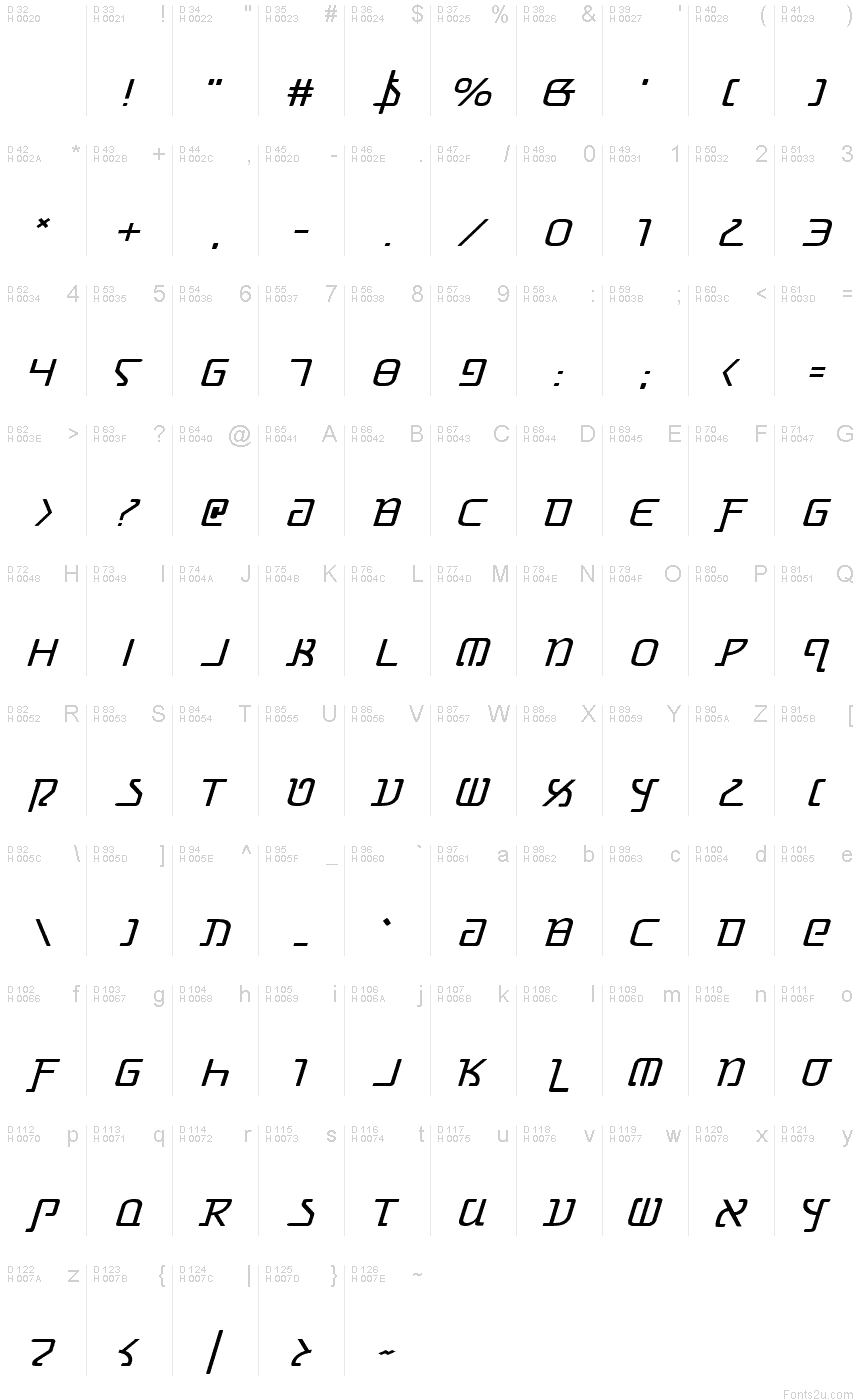
Grimlord Expanded Italic autorstwa Iconian Fonts to darmowy, futurystyczny krój typu display o szerokich, mocno pochylonych kształtach liter. Zaokrąglone zewnętrzne narożniki łączą się z przyciętymi łączeniami oraz otwartymi, kanciastymi cięciami, nadając literom wygląd niestandardowego logo wyścigowego lub science-fiction.
Grafika cyfrowa to idealne środowisko dla jej szybkiej, mechanicznej sylwetki, w szczególności interfejsów gier i wizerunku marek e-sportowych. Sprawdza się również w gadżetach związanych ze sportami motorowymi. W wydawnictwach szerokie formy kursywne mogą nadać okładkom magazynów technologicznych wyraźnie retrofuturystyczny charakter tytułu.